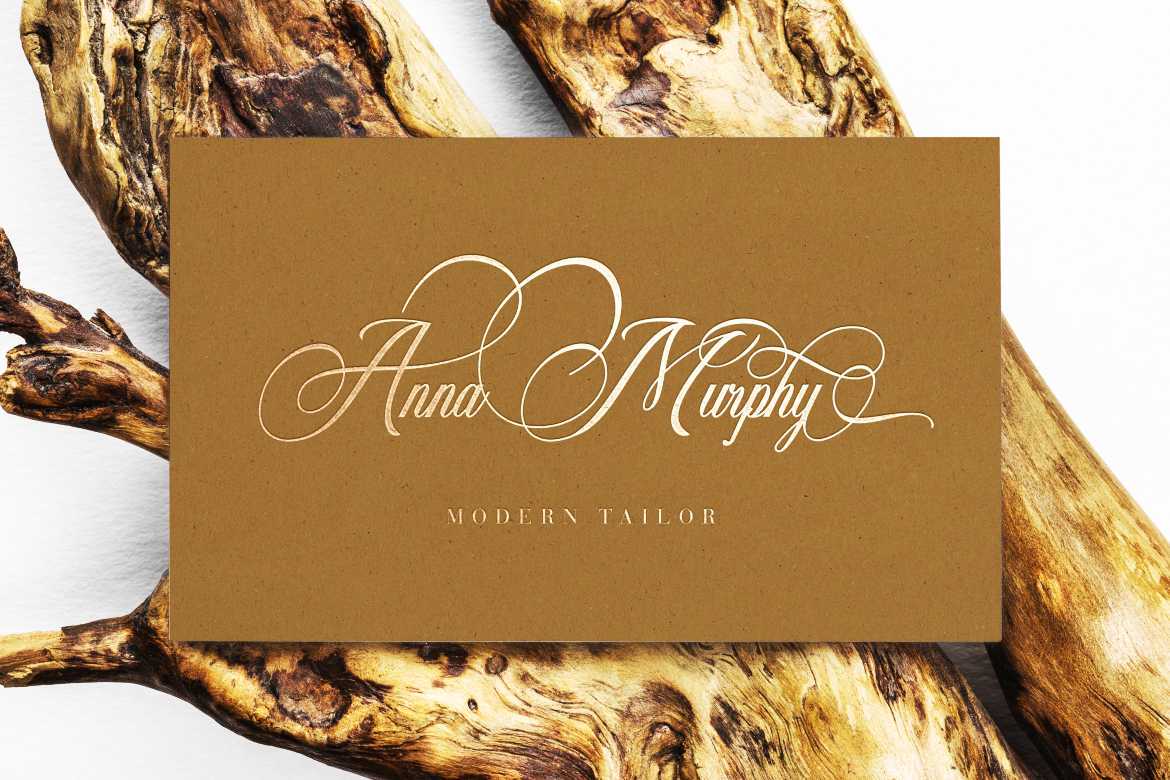
AMORISTAR是一种华丽而独特的显示字体。其中有许多替换字符和连字字符。但是,如果使用Adobe/CoreldRaw,您只需将其中一个字符和箭头显示在文字下方,就可以替换为其他字符。该字体适用于创建徽标、打印模板、海报、品牌、婚礼宣传、报价、,oranythingelse.amorista是一种华丽而独特的显示字体。许多替代字符和连字字符在其内部都是可用的。但是,如果您使用Adobe/CoreldRaw,您只需将其中一个字符和箭头屏蔽在文字下方,就可以用其他字符替换。这种字体非常适合创建徽标、打印模板、海报、品牌、婚礼宣传、报价、,oranythingelse